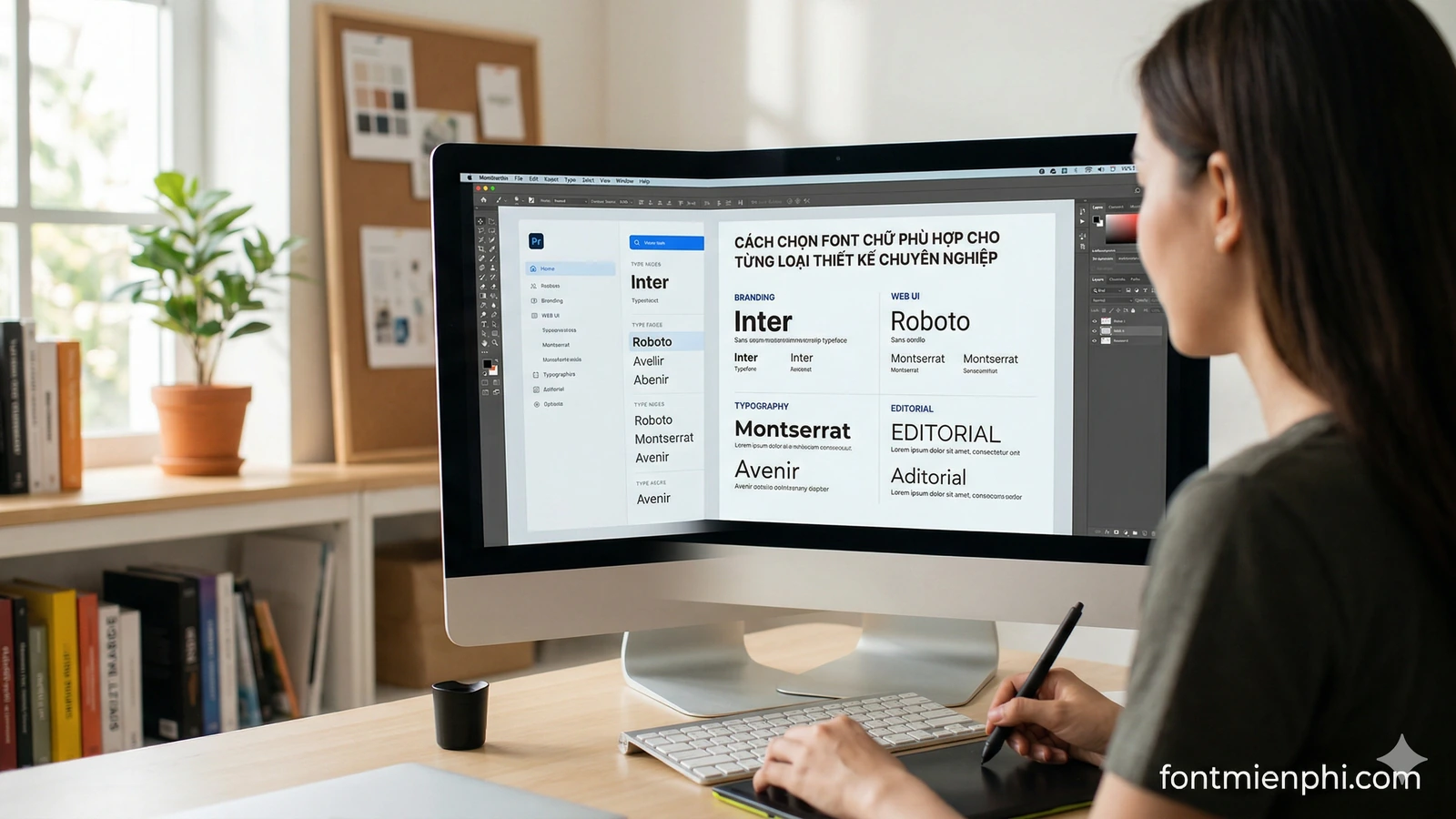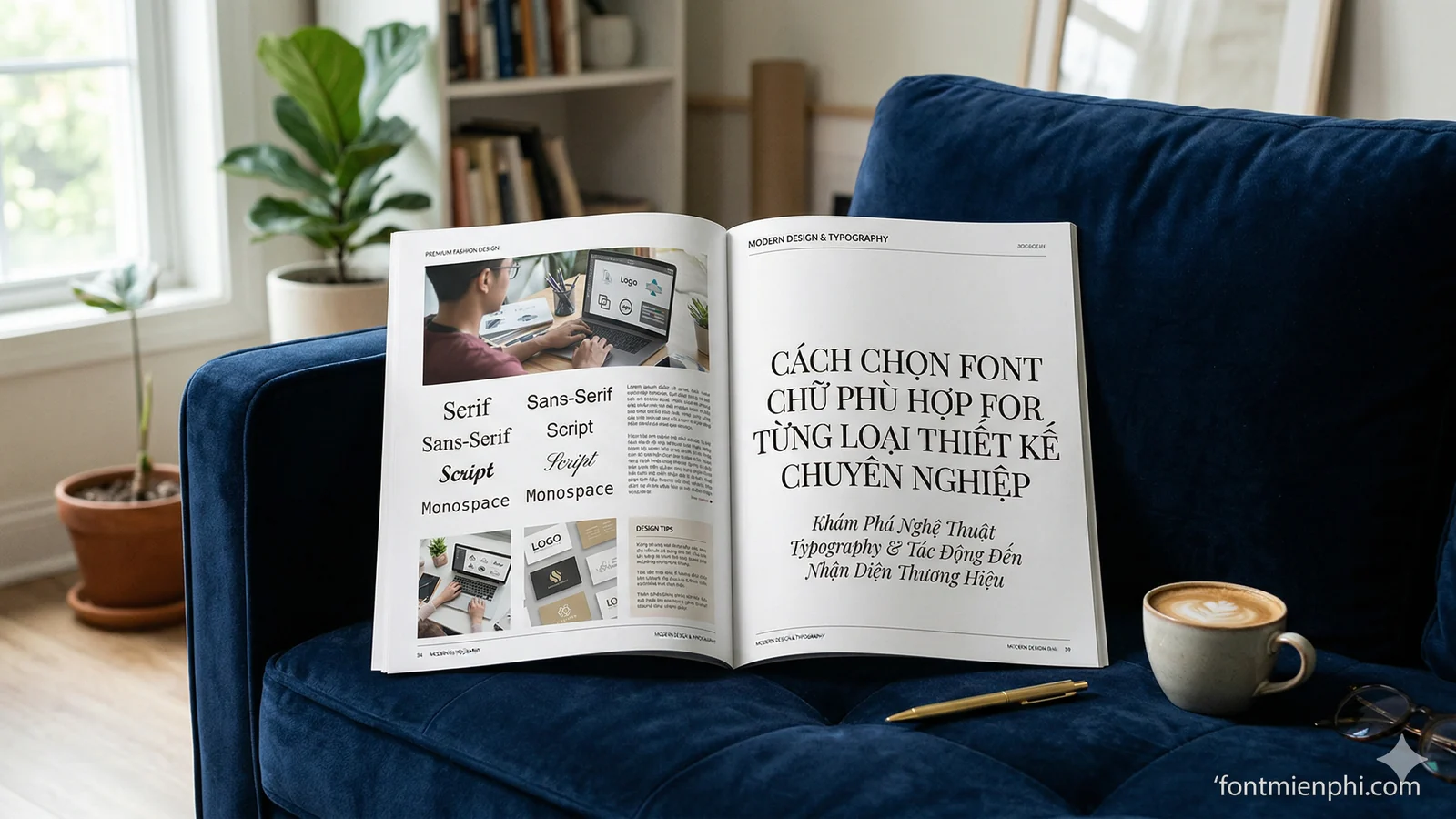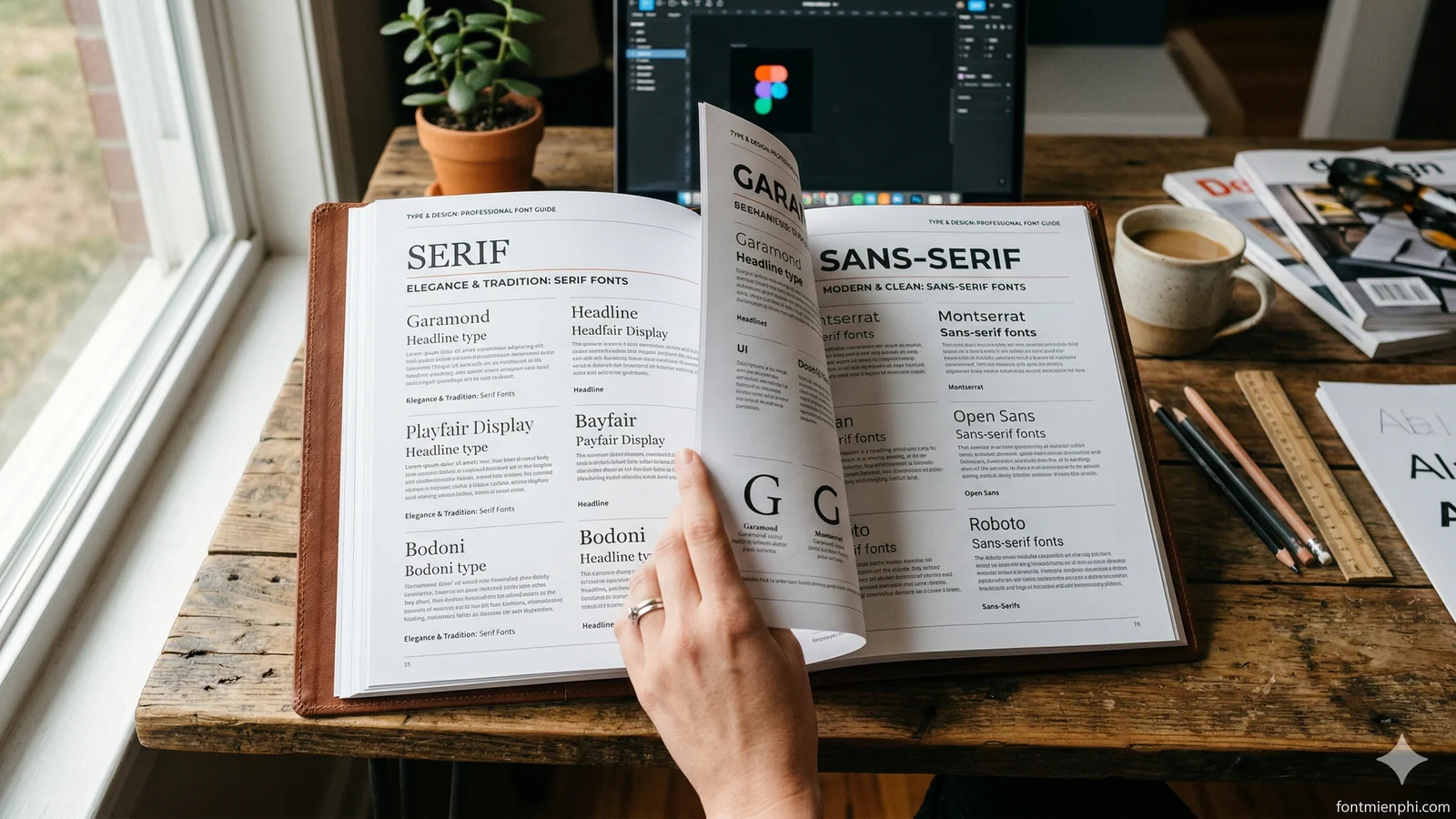
Bài viết hướng dẫn chi tiết cách lựa chọn font chữ hoàn hảo cho mọi loại hình thiết kế chuyên nghiệp. Thông qua việc phân tích tâm lý học typography, phân loại nhóm chữ và nguyên tắc phối hợp, nội dung sẽ giúp bạn áp dụng hiệu quả vào thiết kế logo, website hay ấn phẩm. Đây là nền tảng quan trọng để nâng tầm thẩm mỹ và truyền tải thông điệp thương hiệu.
Trong thế giới của thiết kế đồ họa chuyên nghiệp, typography không chỉ đơn thuần là việc sắp xếp các chữ cái sao cho người xem có thể đọc được văn bản. Nó là một bộ môn nghệ thuật thị giác phức tạp, đóng vai trò như một người kể chuyện thầm lặng, truyền tải cảm xúc, định hình phong cách và xây dựng nhận thức của khán giả về một thương hiệu hoặc một ấn phẩm. Việc lựa chọn đúng font chữ có sức mạnh biến một thiết kế bình thường trở thành một tác phẩm xuất sắc, trong khi một quyết định sai lầm có thể phá hỏng hoàn toàn thông điệp mà nhà thiết kế muốn gửi gắm.
Khi chúng ta nhìn vào một đoạn văn bản, não bộ của chúng ta không chỉ xử lý ý nghĩa của các từ ngữ mà còn tiếp nhận các tín hiệu phi ngôn ngữ từ hình dáng của các ký tự. Đây là lý do tại sao một thông báo pháp lý không bao giờ được viết bằng font chữ uốn lượn bay bướm, và một thiệp mời sinh nhật trẻ em hiếm khi sử dụng những font chữ góc cạnh, cứng nhắc của các văn bản hành chính. Font chữ chính là giọng nói của thiết kế. Nếu hình ảnh và màu sắc thu hút sự chú ý của người xem, thì typography chính là yếu tố giữ chân họ lại và dẫn dắt họ đi qua từng lớp thông tin một cách mượt mà và có chủ đích.
Hơn thế nữa, trong bối cảnh kỷ nguyên số bùng nổ, khi mà lượng thông tin người dùng tiếp nhận mỗi ngày là khổng lồ, tính dễ đọc và tính nhận diện của font chữ trở thành yếu tố sống còn. Các nhà thiết kế chuyên nghiệp phải đối mặt với thách thức không chỉ là chọn một font chữ đẹp mắt, mà còn phải đảm bảo font chữ đó hoạt động hoàn hảo trên nhiều môi trường khác nhau, từ màn hình điện thoại nhỏ bé, màn hình máy tính độ phân giải cao, cho đến các tấm biển quảng cáo ngoài trời khổng lồ hay những trang tạp chí in ấn sắc nét.
Tâm lý học typography là một lĩnh vực nghiên cứu chuyên sâu về cách thức mà các kiểu chữ khác nhau ảnh hưởng đến cảm xúc và hành vi của con người. Mỗi một đường nét, độ cong, độ dày mỏng hay tỷ lệ của các ký tự đều mang theo những ý nghĩa ngầm định. Việc hiểu rõ những yếu tố tâm lý này là chìa khóa để các nhà thiết kế đồ họa và chuyên gia quảng cáo có thể thao túng thị giác và định hướng cảm nhận của người tiêu dùng một cách tinh tế nhất.
Các nghiên cứu đã chỉ ra rằng những font chữ có đường nét bo tròn thường tạo ra cảm giác thân thiện, thoải mái, vui vẻ và dễ gần. Chúng thường được áp dụng trong các thiết kế dành cho trẻ em, các thương hiệu thực phẩm hay các chiến dịch truyền thông mang tính chất cộng đồng. Ngược lại, những font chữ có đường nét thẳng, sắc sảo, góc cạnh lại truyền tải sự mạnh mẽ, quyết đoán, nam tính và đôi khi là sự lạnh lùng, công nghệ. Nhóm font chữ này rất phổ biến trong thiết kế của các thương hiệu thể thao, máy móc kỹ thuật hay các công ty công nghệ cao.
Bên cạnh hình dáng cơ bản, độ dày của nét chữ cũng tác động mạnh mẽ đến tâm lý người xem. Những nét chữ thanh mảnh, mỏng manh thường gắn liền với sự tinh tế, sang trọng, nữ tính và thanh lịch, rất được ưa chuộng trong ngành công nghiệp thời trang cao cấp, mỹ phẩm và trang sức. Trong khi đó, những nét chữ dày, đậm, đặc và nặng nề lại tạo ra cảm giác vững chãi, ổn định, đáng tin cậy và mang tính cảnh báo cao, thường xuất hiện trên các tiêu đề báo chí giật gân, biển báo giao thông hoặc các thông điệp cần sự chú ý ngay lập tức. Sự kết hợp khéo léo giữa các đặc tính vật lý của font chữ sẽ tạo ra một dải cảm xúc phong phú, phục vụ đắc lực cho mục tiêu truyền thông của thiết kế.
Để có thể lựa chọn và phối hợp font chữ một cách chuyên nghiệp, nhà thiết kế cần nắm vững hệ thống phân loại các nhóm font chữ cơ bản. Mỗi nhóm mang những đặc điểm cấu tạo, lịch sử hình thành và ứng dụng thực tiễn hoàn toàn khác biệt.
Serif là nhóm font chữ lâu đời nhất, có nguồn gốc từ những nét khắc trên đá của người La Mã cổ đại và sau đó là những nét cọ trong nghệ thuật thư pháp. Đặc điểm nhận dạng rõ ràng nhất của nhóm này là sự xuất hiện của các nét gạch nhỏ, hay còn gọi là chân, ở các phần đầu và cuối của các nét chữ chính. Các đường nét trong một ký tự Serif thường có độ tương phản cao, nghĩa là có sự chênh lệch rõ rệt giữa nét thanh và nét đậm.
Về mặt tâm lý, font chữ Serif mang đến cảm giác truyền thống, cổ điển, tôn trọng, học thuật và vô cùng đáng tin cậy. Chính vì thế, nhóm font chữ này thường được sử dụng làm văn bản chính trong các cuốn sách, báo in truyền thống, tạp chí học thuật, hoặc trong logo của các trường đại học, ngân hàng, công ty luật và các thương hiệu cao cấp có bề dày lịch sử. Các nét chân của chữ Serif không chỉ mang ý nghĩa trang trí mà còn có tác dụng dẫn dắt ánh mắt người đọc di chuyển theo chiều ngang, giúp việc đọc các đoạn văn bản dài trên giấy trở nên dễ dàng và ít gây mỏi mắt hơn.
Trái ngược với Serif, nhóm Sans-serif bao gồm những kiểu chữ đã loại bỏ hoàn toàn các nét gạch chân trang trí. Từ Sans trong tiếng Pháp có nghĩa là không. Các font chữ thuộc nhóm này thường có cấu trúc hình học rõ ràng, các nét chữ có độ dày khá đồng đều và mang lại một diện mạo vô cùng sạch sẽ, gọn gàng, mang đậm hơi thở của chủ nghĩa hiện đại. Sự ra đời và phổ biến của Sans-serif gắn liền với phong trào thiết kế Bauhaus và sau này là sự bùng nổ của kỷ nguyên kỹ thuật số.
Font chữ Sans-serif đại diện cho sự hiện đại, tối giản, trực tiếp, cởi mở và tính công nghệ. Với cấu trúc đơn giản, chúng hiển thị cực kỳ sắc nét trên các thiết bị điện tử có độ phân giải thấp, giúp hạn chế tình trạng vỡ nét hay nhòe mờ. Do đó, Sans-serif gần như thống trị hoàn toàn lĩnh vực thiết kế giao diện người dùng, thiết kế website, ứng dụng di động và các định dạng quảng cáo kỹ thuật số. Chúng cũng là sự lựa chọn hàng đầu cho các công ty khởi nghiệp công nghệ, các thương hiệu thời trang hiện đại hướng tới sự tối giản và năng động.